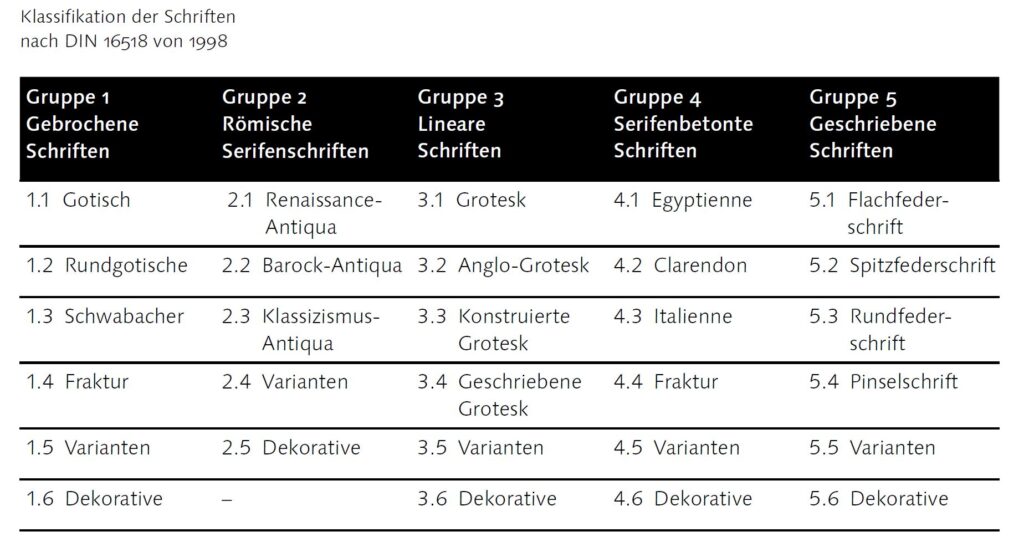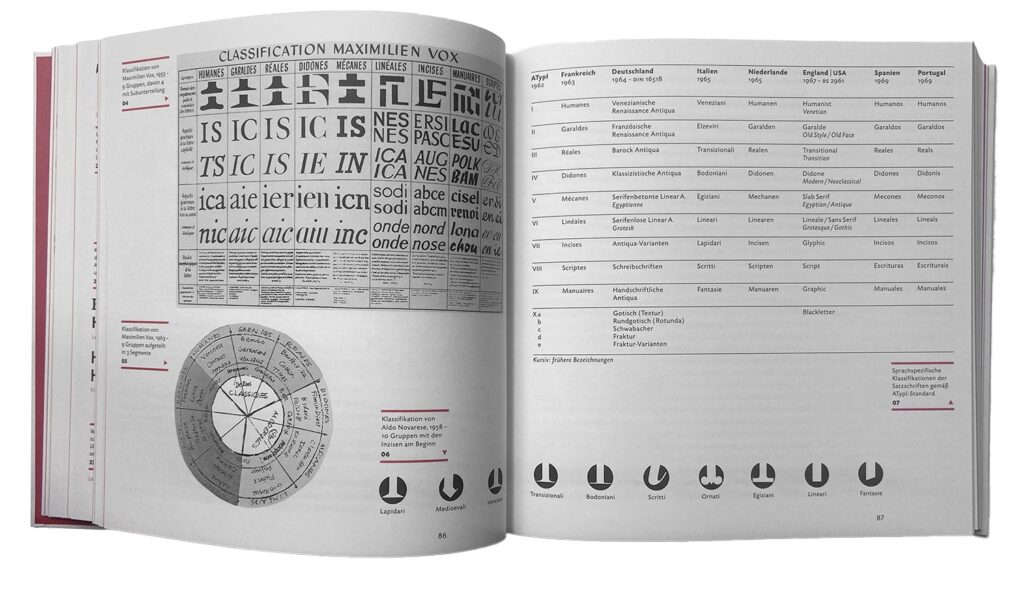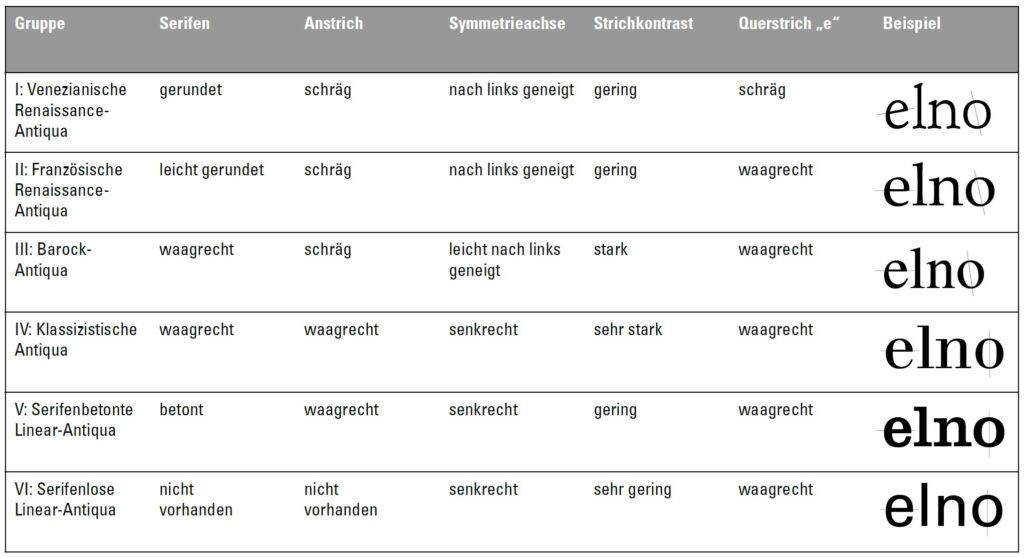
Schriftklassifikation
Die heutigen Schriftklassen orientieren sich oft an Epochen der Schriftgeschichte, ursprünglich sollten sie jedoch vor allem den Stil einer Schrift erfassen – unabhängig von ihrer Entstehungszeit. Klassifikationen dienen der Einordnung, Pflege und Kombination von Schriften. Sie helfen, harmonische Mischungen zu gestalten und unpassende Kombinationen – etwa Renaissance- und Barock-Antiqua – zu vermeiden.
Die DIN-Klassifikation
Ein bedeutendes System ist die DIN 16518 von 1964, entwickelt vom Deutschen Institut für Normung für den Bleisatz. Sie unterscheidet elf Stilrichtungen. Trotz technischer Weiterentwicklungen, Kritik und einer Überarbeitung 1998 wird die ursprüngliche Klassifikation bis heute gelehrt und verwendet.